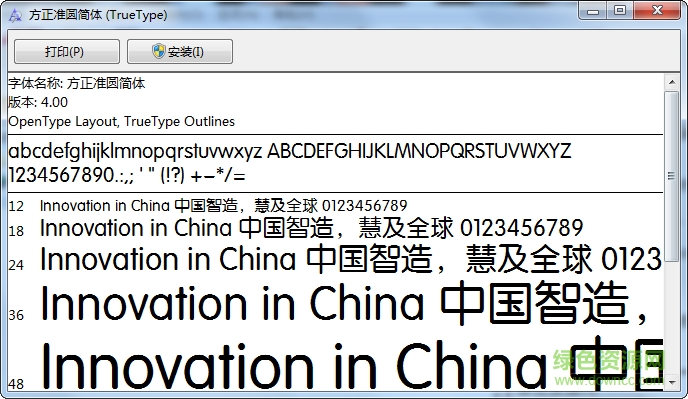
zhunyuan字體是一款支持中英文輸入的準(zhǔn)圓字體,比例勻稱,大小適中,可適用范圍廣泛,mac系統(tǒng)和Windows系統(tǒng)都可以使用,需要的朋友快來(lái)綠色資源網(wǎng)下載吧!
圓體,開頭結(jié)尾都比較圓,原題還分為西原題和粗圓體,它們的特征與圓體相似,就是比例不一樣。